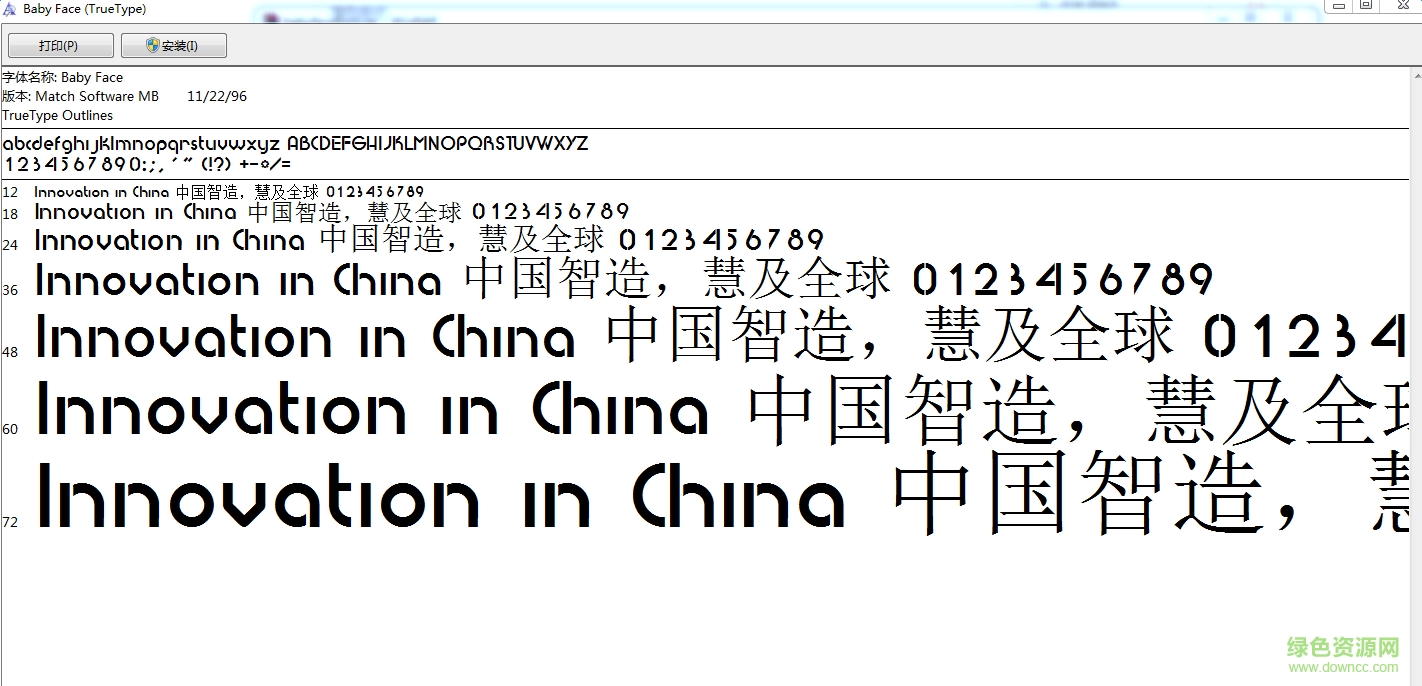
babyface字體是一款babyface風(fēng)格英文字體軟件,babyface風(fēng)格的字體給人非常舒服的感覺(jué),深受廣大年輕人的喜愛(ài),還有更多好看字體盡情期待,歡迎到綠色資源網(wǎng)下載體驗(yàn)!
babyface是一款babyface風(fēng)格英文字體,字體效果比較好看,喜歡英文體字的朋友可以下載使用看看效果如何。